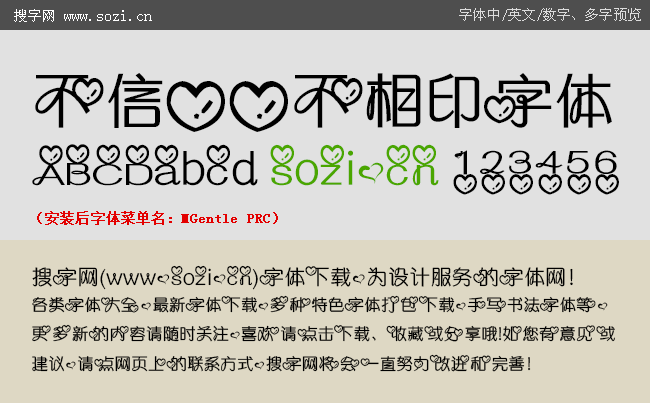
不信心心不相印字體
搜字網(wǎng)給大家提供一款很萌的卡通手機(jī)中文字體下載。這款手機(jī)字體叫不信心心不相印字體,這款字體筆畫由蒙納纖蘭體為原形,在字體中插入卡通心形圖案,蒙納纖蘭體字形端正大方,通過(guò)心形點(diǎn)綴帶來(lái)一點(diǎn)童趣,擁有童心的可愛(ài)萌友們快快下載吧。